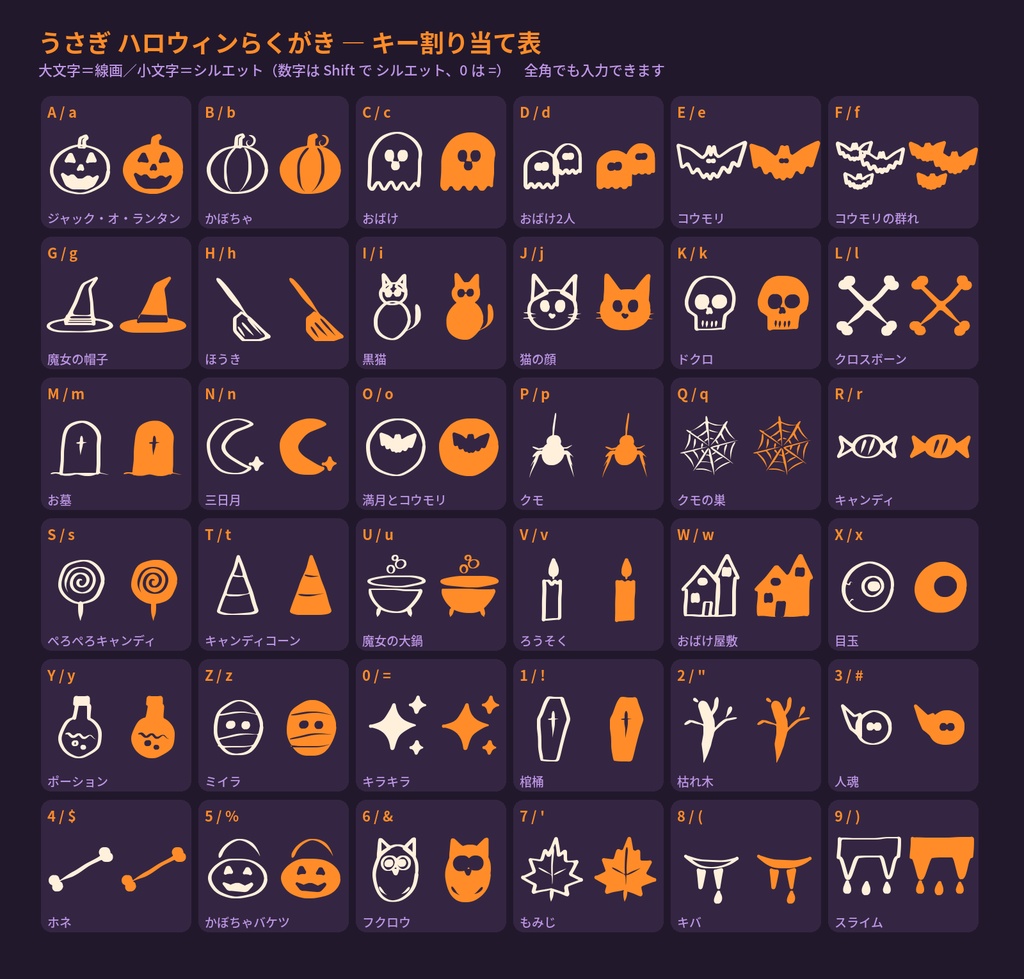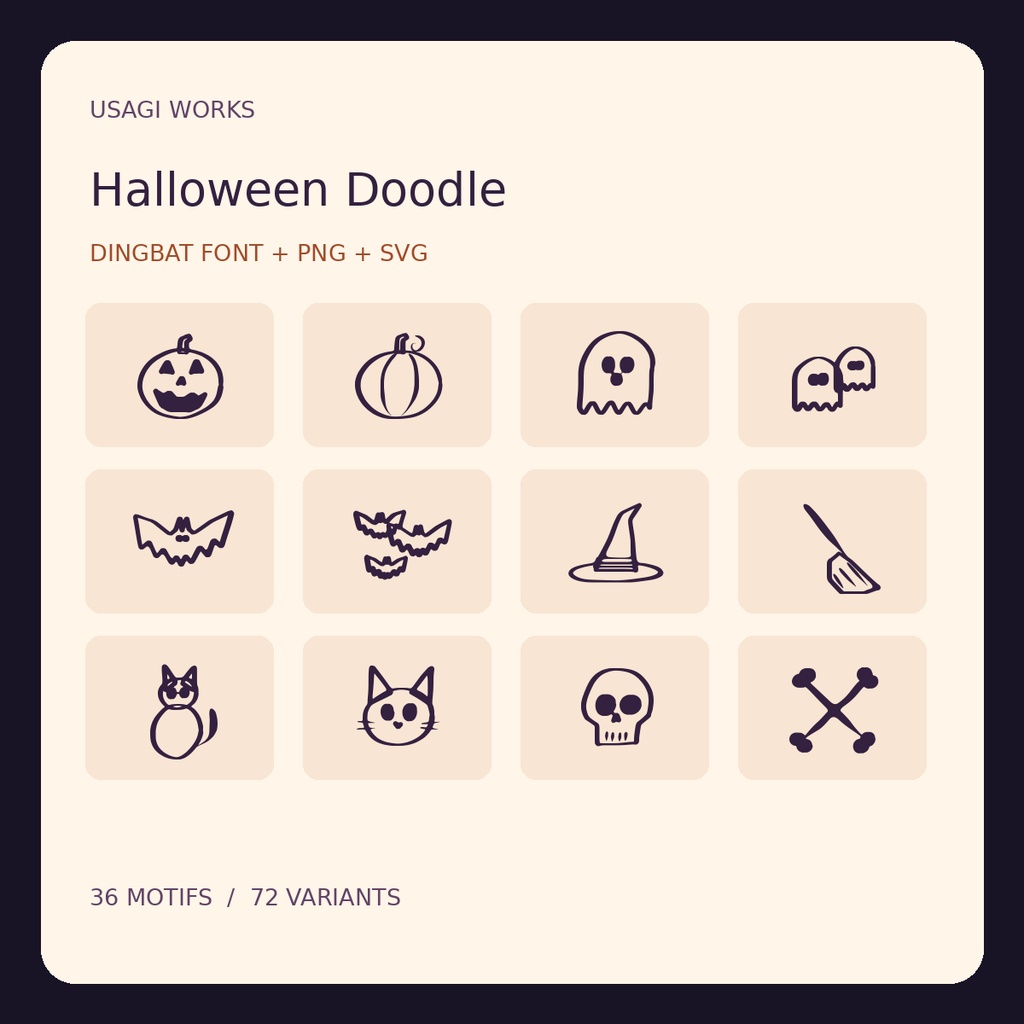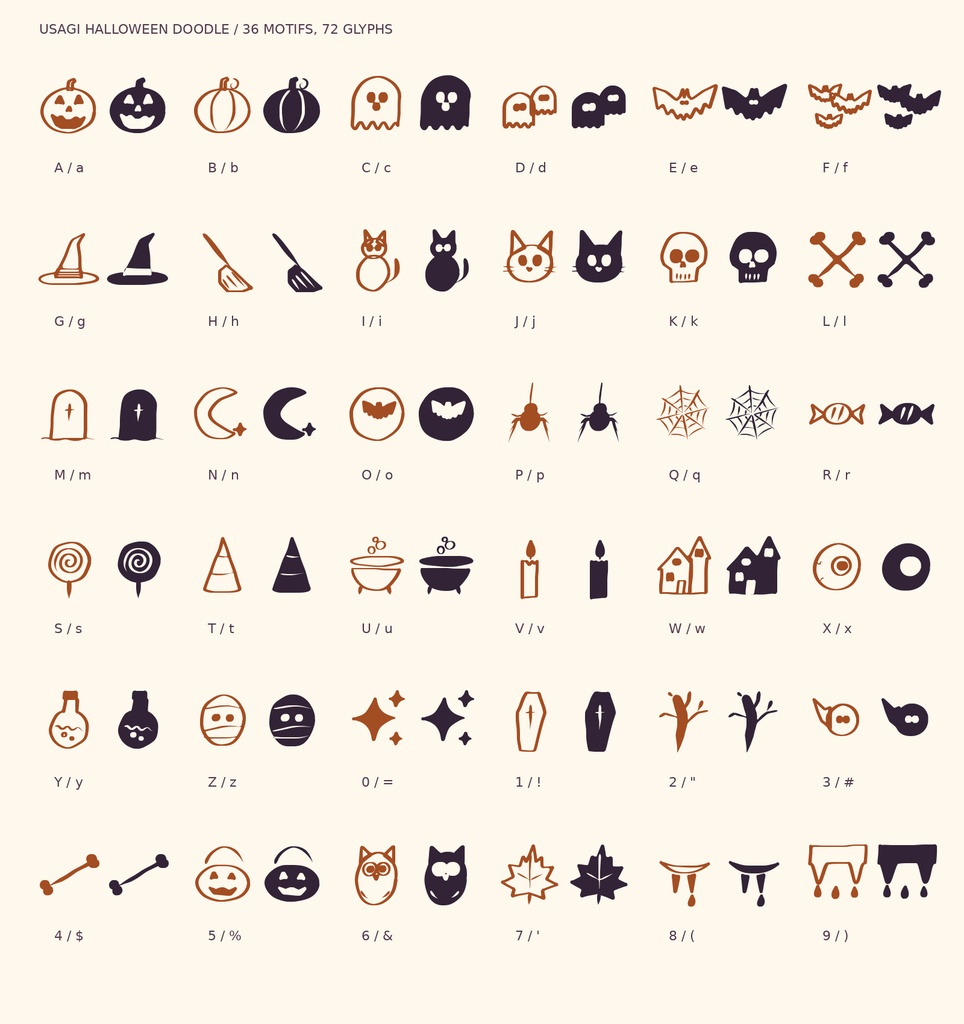
うさぎ ハロウィンらくがき|手描き記号フォント+透過PNG・SVG 72点
【Usagi Halloween Doodle v1.0.1】 おばけ、かぼちゃ、黒猫、コウモリなど、ハロウィンのモチーフを集めた手描きイラストフォント&素材セットです。 36種類のモチーフを線画・シルエットの2スタイルで収録。キーボードからイラストを呼び出せるTTFフォントに加え、透過PNG・SVG素材も合計72点付属しています。 ■ 収録内容 ・TTF記号フォント:1本 ・透過PNG素材:72点 ・SVG素材:72点 ・キー割り当て表 ・README/利用規約 ■ おすすめの用途 ハロウィンのポスター、チラシ、SNS投稿画像、動画、ゲーム、同人誌、招待状、ラベル、季節の装飾など。 ■ ご購入前に 本商品は、英数字を通常の文章として表示するフォントではありません。キー入力でイラストを表示する「記号フォント」です。対応するキーは付属の一覧表をご確認ください。 ■ 利用規約 個人・商用利用は同梱の利用規約の範囲で可能です。フォント・素材そのものの再配布や転売は禁止しています。詳細は同梱規約をご確認ください。 ※デジタルダウンロード商品です。実物の発送はありません。 ※ソフトウェアによって対応するフォント・画像形式が異なります。 制作:USAGI WORKS お問い合わせ:kanpatree2+usagiworks@gmail.com